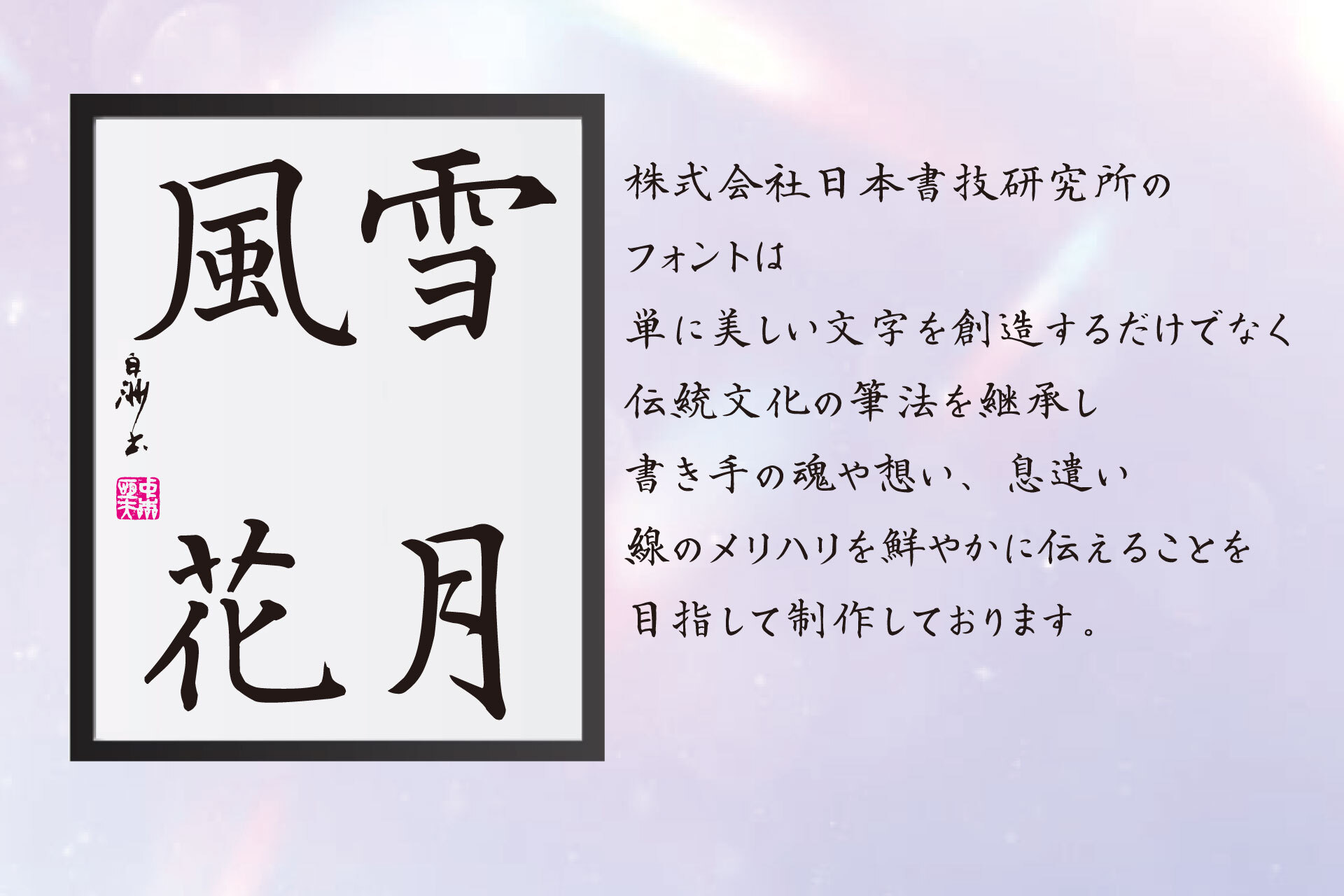
フォントサービス「フォントワークスLETS」に日本書技研究所の9書体、RENFONTを1書体を追加
米国 Monotype Imaging Inc.の日本法人Monotype株式会社(東京都港区、以下 Monotype)は、日本のタイプファウンダリ 日本書技研究所と提携。Monotypeが提供する年間定額制フォントサービス「LETS Leading Edge Type Solution」のライブラリ「フォントワークス LETS」および「学生向けフォントワークス LETS」、ならびにWebフォントサービス「FONTPLUS」に計9書体の提供を、2025年5月27日(火)より開始しました。日本書技研究所によるMonotypeへの書体提供は、今回が初となります。
また同日、REN FONTからも1書体が追加となりました。
日本書技研究所の9書体を追加
| 【日本書技研究所のご紹介】 タイプデザイナー:中本 白洲 石橋犀水に師事し、書道家として活躍。毛筆フォント開発も多数手掛け、海外でも作品が紹介されるなど、日本のみならず世界に書を発信し続けている。 書道家の草分け的存在として、NHK教育テレビ「100分で名著」への出演4回をはじめ、テロップや題字の揮毫、テレビ番組や雑誌への掲載など、メディアでも活躍。 |
白洲願法体について(日本書技研究所より)
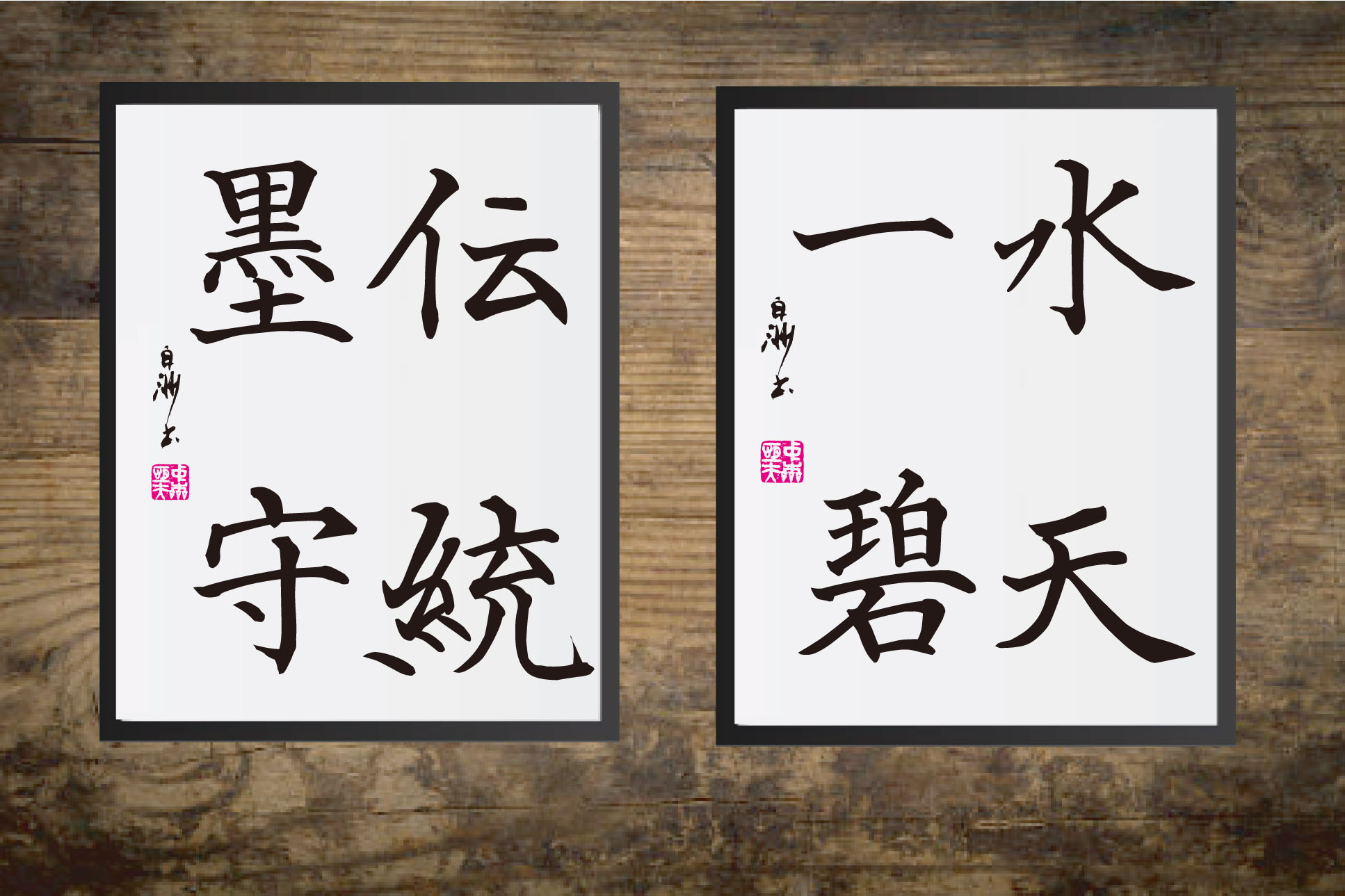
この書体は、中国唐代に活躍した顏真卿の書風を再現。
肉太で充実した線質が特徴。文字を少し左旋回に表現にて動的表現をしながら、安定感と、力強く堂々とした印象を表現。構図は向勢を持ち肉太で充実した線質が特徴。この書体ファミリーの非漢字は、それぞれ独自の文字幅を持つプロポーショナル字形としてデザインされています。
白洲真楷書体について(日本書技研究所より)
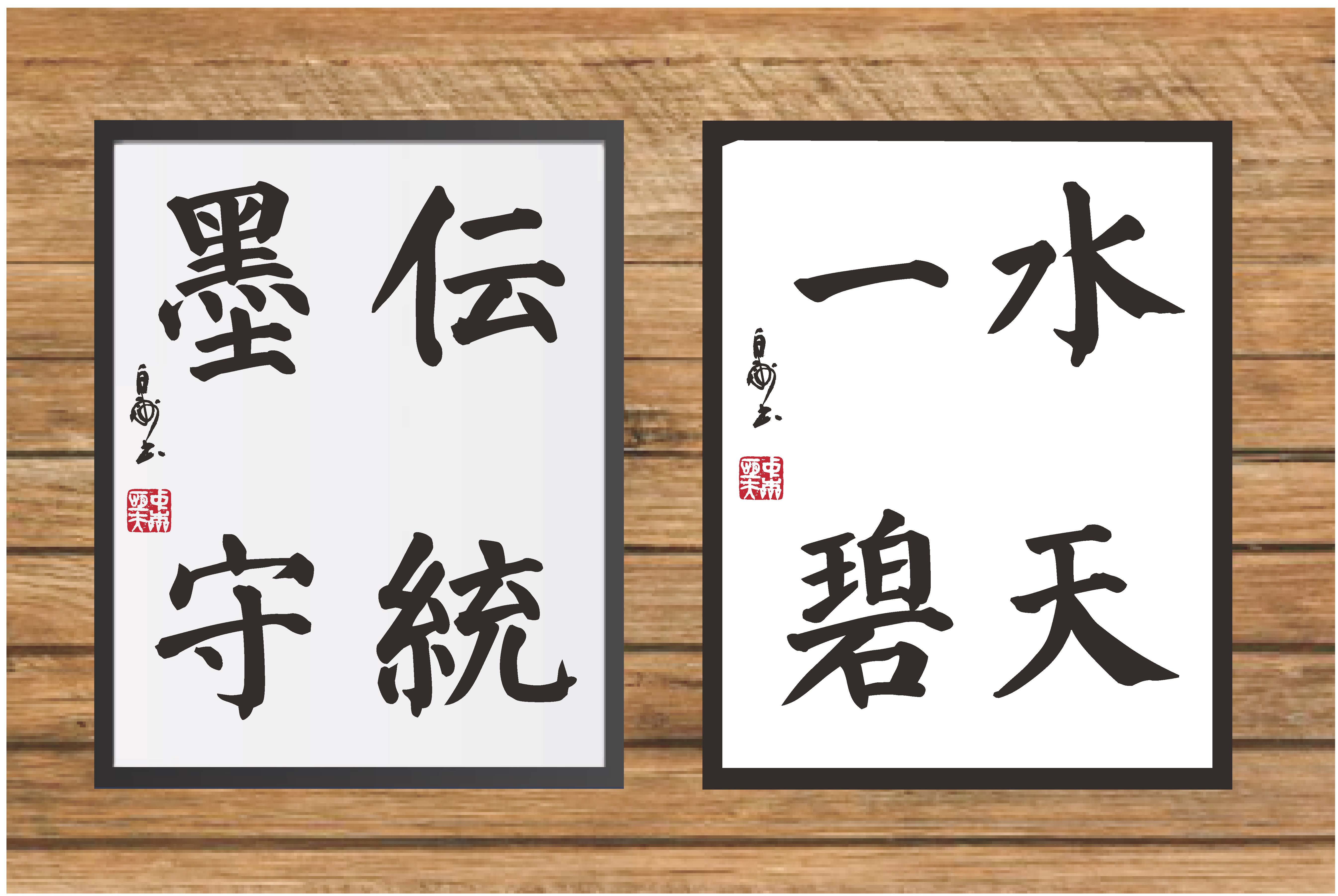
真楷書は、美文字を意識しながら 起筆と収筆の丁寧な表現、文字の長短や強弱への細やかな注意が払われています。その結果、生き生きとした線と美しい字形が実現され、手書きならではの温かみが感じられる仕上がりとなっています。この書体ファミリーの非漢字は、それぞれ独自の文字幅を持つプロポーショナル字形としてデザインされています。
【提供書体一覧】
| 書体名 | ウェイト |
| 白洲願法体(はくしゅうがんほうたい) | W1 / W3 / W6 / W9 |
| 白洲真楷書体(はくしゅうしんかいしょたい) | W1 / W3 / W6 / W9 / W12 |
フォントワークス LETSに提供中のREN FONT書体に「奔行2かな-L」を追加
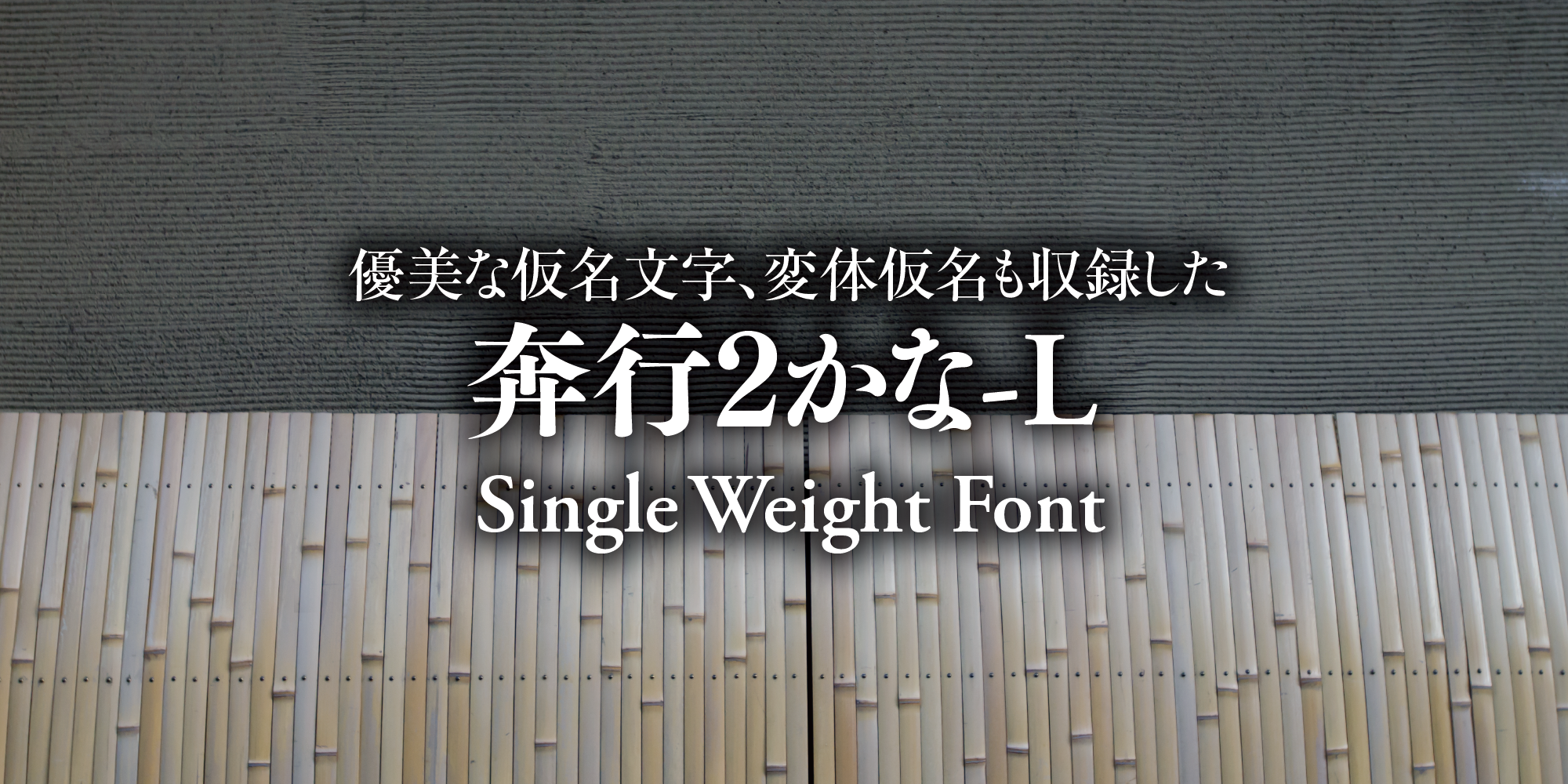
フォントワークス LETSへ、新たに「奔行2かな-L」を追加しました。 今回の書体追加で合計83書体のREN FONT書体がご利用いただけます。
優美な仮名文字、変体仮名も収録
奔行2かな-Lは、特定非営利活動法人日本タイポグラフィ協会により開催された、2004年度「日本タイポグラフィ年鑑2004」コンテストの書体部門入選作「勢蓮奔行-L」を源流とし、制作されています。
平仮名、片仮名、欧文、記号類、変体仮名の各字種を収録し、楷書から行書へ崩す書法の中間レベルの筆致を全文字で展開、書の奔放さを表現しました。 また、変体仮名は、現代仮名各文字に対応する異体字として容易に呼び出すことができます。さらに、Unicode(一部文字種)にも対応しました。この変体仮名は現代仮名と違和感の少ない整形を施しており、新旧かなの混在ができる、独創的な書体となっています。
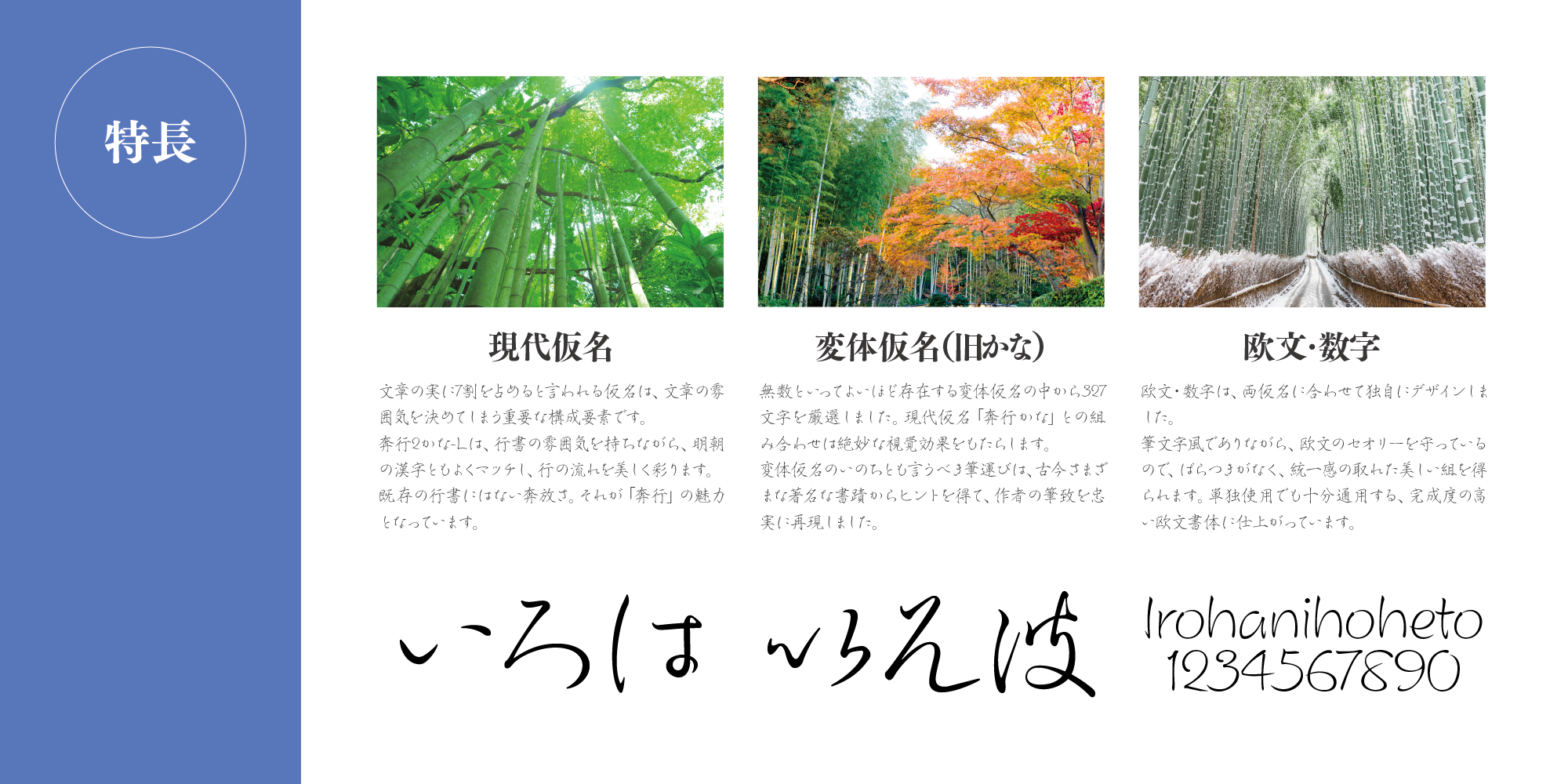
奔行2かな-Lには拗音・促音・濁音および「ん」以外の全ての各現代仮名の「音」に対応した変体仮名が327文字追加装備されております。変体仮名のUnicode対応、横組み・縦組みにプロポーショナル・ペアカーニング処理など、機能を充実しました。
なお「奔行かなStd-L」との互換性はありません。